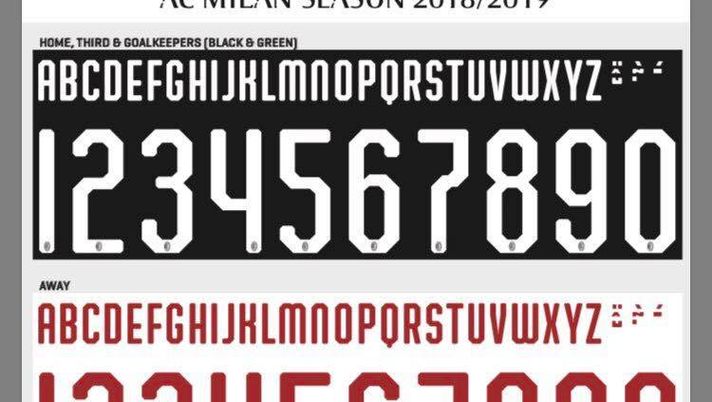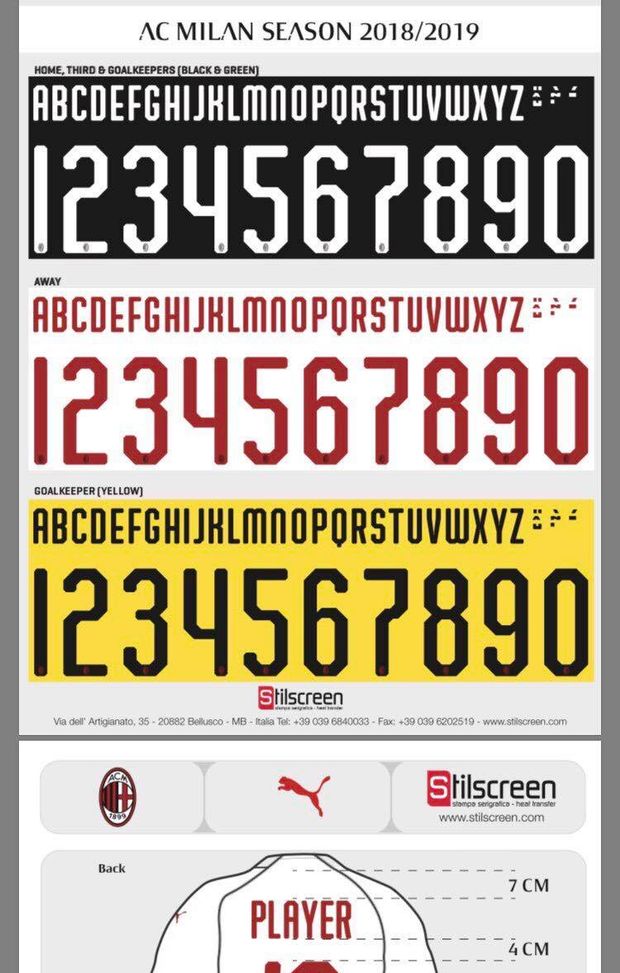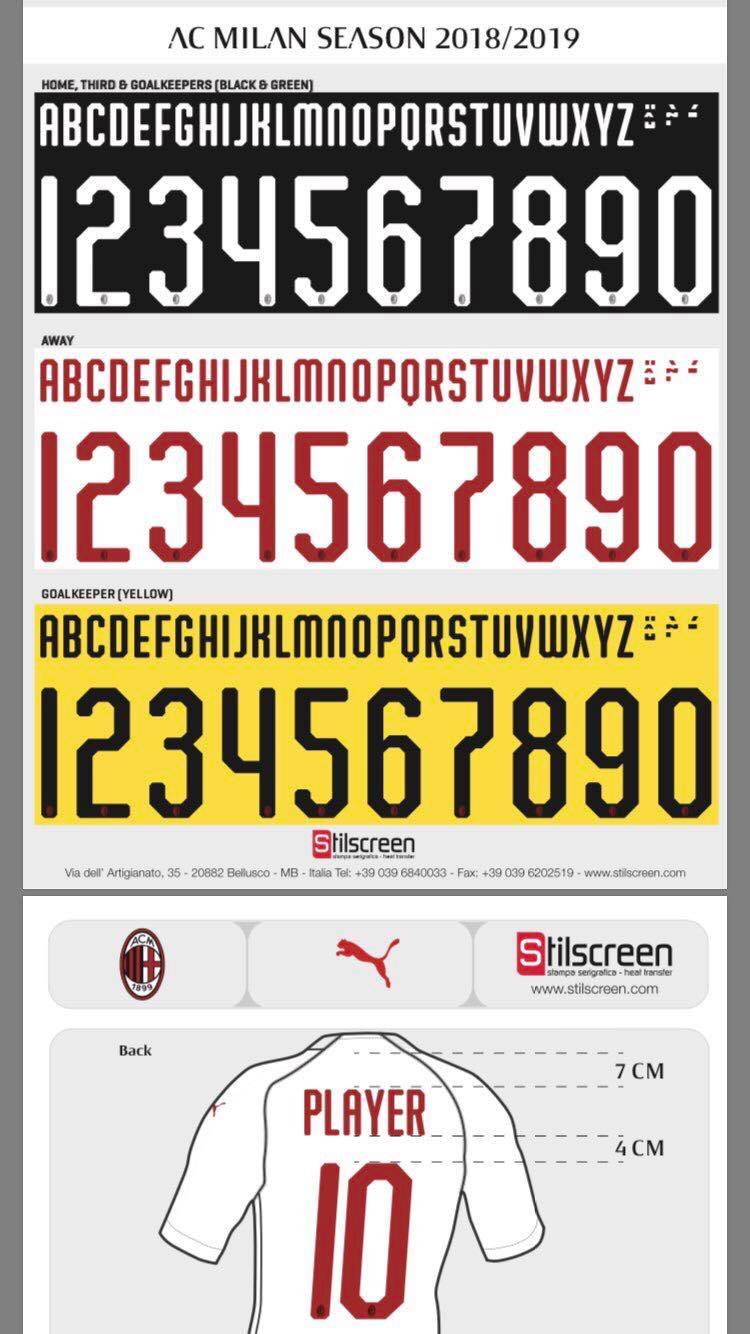
Dal primo luglio è ufficialmente iniziata la partnership tra il Milan e la Puma. Il 6 saranno presentate le nuove maglie, intanto ecco il font dei numeri.
Dopo circa vent'anni il Milan non sarà più legato ad Adidas. Il brand tedesco ha infatti deciso di rescindere il proprio contratto con il club rossonero, che ha così virato sulla Puma. Dal primo luglio, con l'inizio della nuova stagione, è iniziata ufficialmente anche la nuova partnership. Tuttavia, la nuova maglia del Milan sarà presentata il 6 luglio. Nel frattempo, su internet sono comparse le immagini del font di nomi e numeri sulle maglie dei giocatori. Molto simile al classico stile della Puma adottato anche per le Nazionali ai Mondiali e per l'Italia stessa, ma con qualche lieve differenza. Sono state rese note anche le distanze: il nome sarà staccato 7cm dal collo, mentre tra nome e numero ci saranno 4cm. Saranno bianchi su prima e terza maglia, oltre che su quella verde e su quella nera da portiere; mentre saranno rossi su quella da trasferta (classica bianca); infine saranno neri su quella gialla da portiere. Se vuoi scoprire in anteprima la nuova maglia, clicca qui.